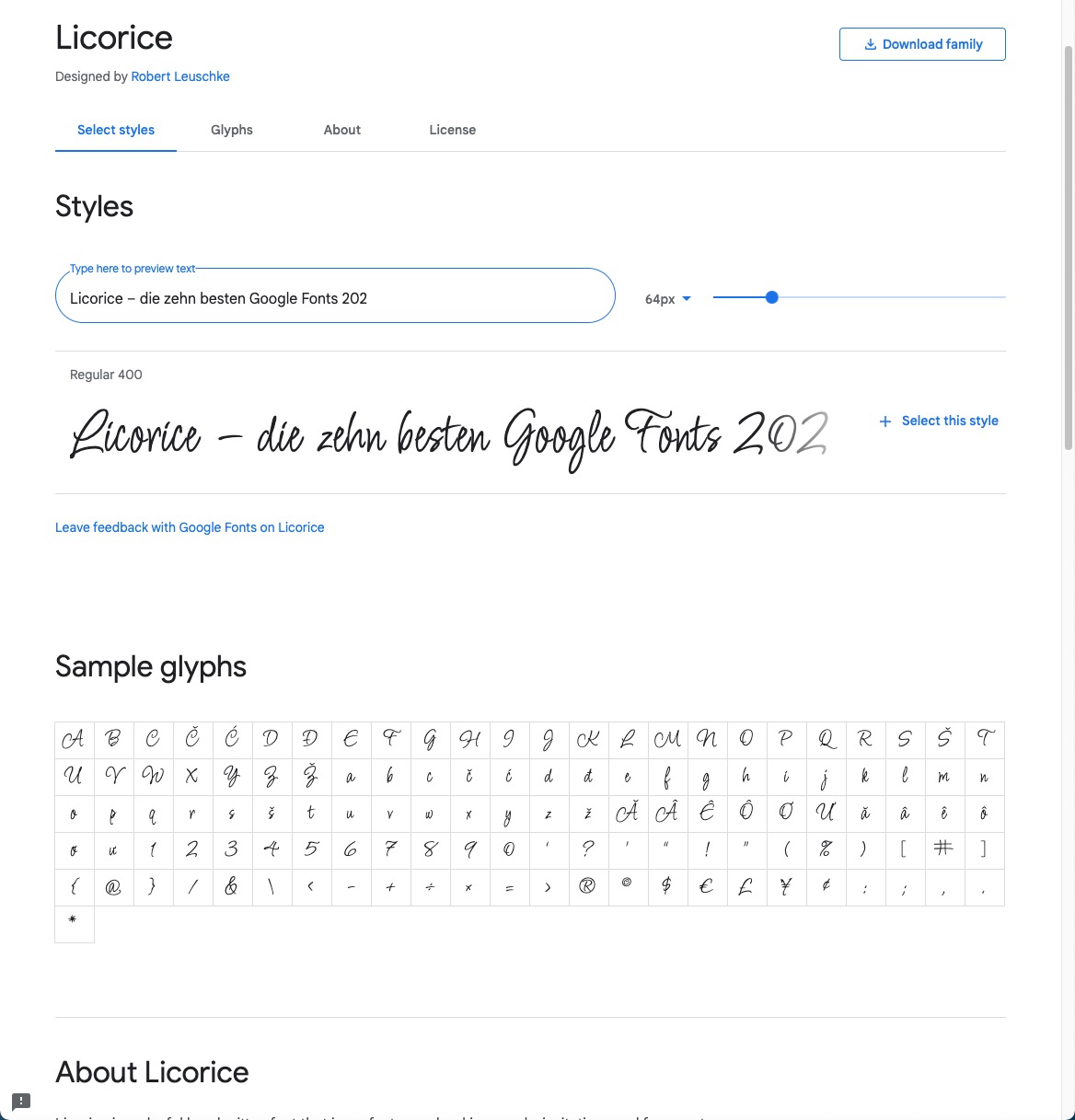
Sucht man in Suchmaschinen nach kostenlosen Schriften für seine Gestaltungen, muss man sich zumindest keine Sorgen machen, zu wenig Treffer zu bekommen. „Fonts for free“ bringt auf die Schnelle bei Google über 19 Milliarden Treffer. Die Kunst ist nun, neben der stilistisch passenden Schrift auch eine technisch saubere und qualitativ gute Schriftart zu finden.
Dabei endet die Suche oft beim Schriftportal von Google; dort sind knapp 1.000 Schriften kostenlos verfügbar, die sich nicht nur bei Webmastern großer Beliebtheit erfreuen. Der Grund dafür ist nicht nur, dass die Schriften kostenlos sind und einfach per CSS eingebunden werden können. Vor allem sind sie auch qualitativ hochwertig und halten einer genaueren typografischen Betrachtung stand.
Wir stellen Ihnen für 2020 die zehn – unserer Meinung nach – besten Google-Fonts vor, die allesamt kostenlos und ohne Einschränkungen verwendbar sind. Da „Open Sans“ und „Roboto“ relativ bekannt sein dürften, haben wir uns vor allem um die etwas unbekannteren und neueren Fonts gekümmert, gewissermaßen einige „Geheimtipps“ zusammengestellt. Wir hoffen, dass für Sie etwas dabei ist.
1. Alegreya Sans
Die Alegreya Sans ist eine humanistische serifenlose Google-Font, die sehr lebendig wirkt. Der Designer Juan Pablo del Peral hat ihr einen Hauch von Wechselstrichattitüde gegeben, und so wirken manche Bögen, wie die im unteren Teil vom kleinen „a“, sympathisch und kantig. Besonders bei der kursiven Variante zeigen sich die gebrochenen Bögen und der Wechselstrichcharakter deutlich stärker. Die Zahlen weisen Ober- und Unterlängen auf, was ebenfalls Bewegung in den Google-Font bringt. Die Familie besteht aus dem normalen und dem kursiven Schriftschnitt in jeweils sieben Varianten.
2. B612
Die serifenlose Schriftart B612 wurde für den Einsatz im Flugzeug-Cockpit getestet und entwickelt. Somit eignet sich der Google-Font optimal dafür, die üblichen Müdigkeitserscheinungen beim Lesen am Monitor möglichst gering zu halten. Trotzdem ist er weniger nüchtern und neutraler als zuerst vermutet. Leichte Schrägen, wie bei „A“ oder „L“, sowie kleine Lücken in den Übergängen, bei „K“ oder „R“ sorgen für die nötige Individualität. Mit vier Schriftschnitten Regular, Regular Italic, Bold und Bold Italic ist die Grundausstattung gesichert. Zusätzlich wird die B612 durch die B612 Mono als monospaced-Variante ergänzt.
3. Cormorant
Inspiriert von Claude Garamond, hat Christian Thalmann mit der Cormorant eine wunderschöne Serifenschrift entwickelt. Die elegante Wirkung verdankt der Google-Webfont unter anderem auch in der Bold-Variante vorhandenen feinen Wechselstrichen.
Wer nach den zehn Schriftschnitten der normalen Variante noch mehr Cormorant möchte, findet noch sechs weitere Styles, darunter eine Kapitälchen- und eine Upright-Variante. Unser Tipp: Am besten mischt man nur die Schnitte, die sich optisch genug voneinander unterscheiden.
4. Fira Sans
Die Fira Sans ist einer der Klassiker unter den Google-Fonts und ein echter Allrounder. Als kleine Schwester der Schriftart „Meta“ von Erik Spiekermann wurde sie ursprünglich als Webfont für die OS-Variante von Firefox entwickelt. Durch ihren serifenlosen, neutralen und klaren, aber nicht zu clean wirkenden Charme hat sie zu Recht viele Anhänger gefunden. Inklusive der Condensed-Variante kommt man bei diesem Google-Font auf ganze 36 Schriftschnitte.
5. IBM Plex
Die IBM Plex ist eine zeitlose und klassische Serifenlose. Die Entwicklung dieser Schrift beruht auf der Geschichte von IBM und der Beziehung zwischen Mensch und Maschine. Ihre Lesbarkeit ist – unabhängig vom Medium – sehr hoch und wer den Google-Font mit Serif- und Sans-Condensed-Variante ergänzen will, kommt auf insgesamt 42 Schnitte.
6. News Cycle
Die News Gothic ist sicher jedem schon einmal ins Dokument gerutscht. Der Google-Font News Cycle ist eine Weiterentwicklung hiervon. Vor allem durch klare, schmale Formen gewinnt dieser Font eine Menge Sympathien. Mit nur zwei Schriftschnitten sind die Variationsmöglichkeiten allerdings sehr beschränkt.
7. Pacifico
Bei der Pacifico hat sich ursprünglich Vernon Adams von der amerikanischen Surfkultur der 1950er-Jahre inspirieren lassen. Jacques Le Bailly überarbeitete den Font von Vernon Adams und herausgekommen ist eine handschriftliche Pinselschrift mit nahezu gleichbleibender Strichstärke, die mit ihren harmonischen Rundungen voller Elan steckt. Bei diesem Google-Font gibt es jedoch nur einen Schriftschnitt.
8. PT Serif
Die PT Serif wurde genau wie ihre ältere, serifenlose Schwester PT Sans für ein russisches Projekt entwickelt. Sie hat humanistische Züge und somit einen leichten handschriftlichen Charakter im Gegensatz zu Schriften, die sehr konstruiert wirken. Mit seinen vier Schnitten ist der Google-Font breit einsetzbar. Wer noch mehr Fonts kombinieren möchte, ergänzt die PT Serif mit der PT Sans, die sich harmonisch einfügt.
9. Roboto Slab
Wie eingangs erwähnt, ist die Roboto hinlänglich bekannt. Sie hat ein klares Schriftbild und wirkt trotz ihrer weitgehend auf geometrischen Formen basierenden Zeichen nicht künstlich oder konstruiert. Nicht nur deshalb hat der Font inzwischen viele Freunde gefunden.
Mehr Google-Fonts gefällig? In unserem Artikel „Zehn angesagte Script Fonts von Google“ verraten wir, welche Schreibschrift-Varianten uns am besten gefallen haben.